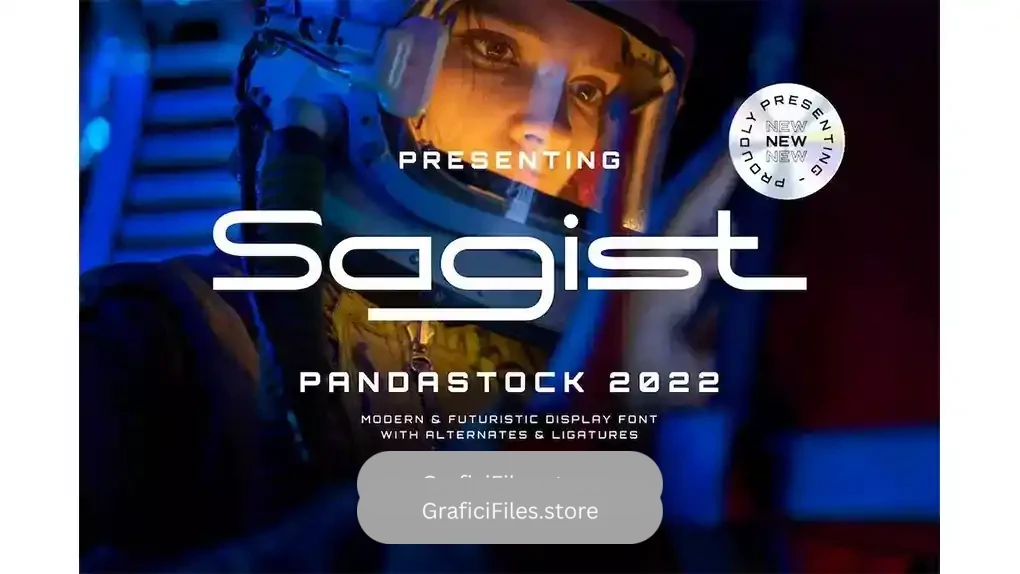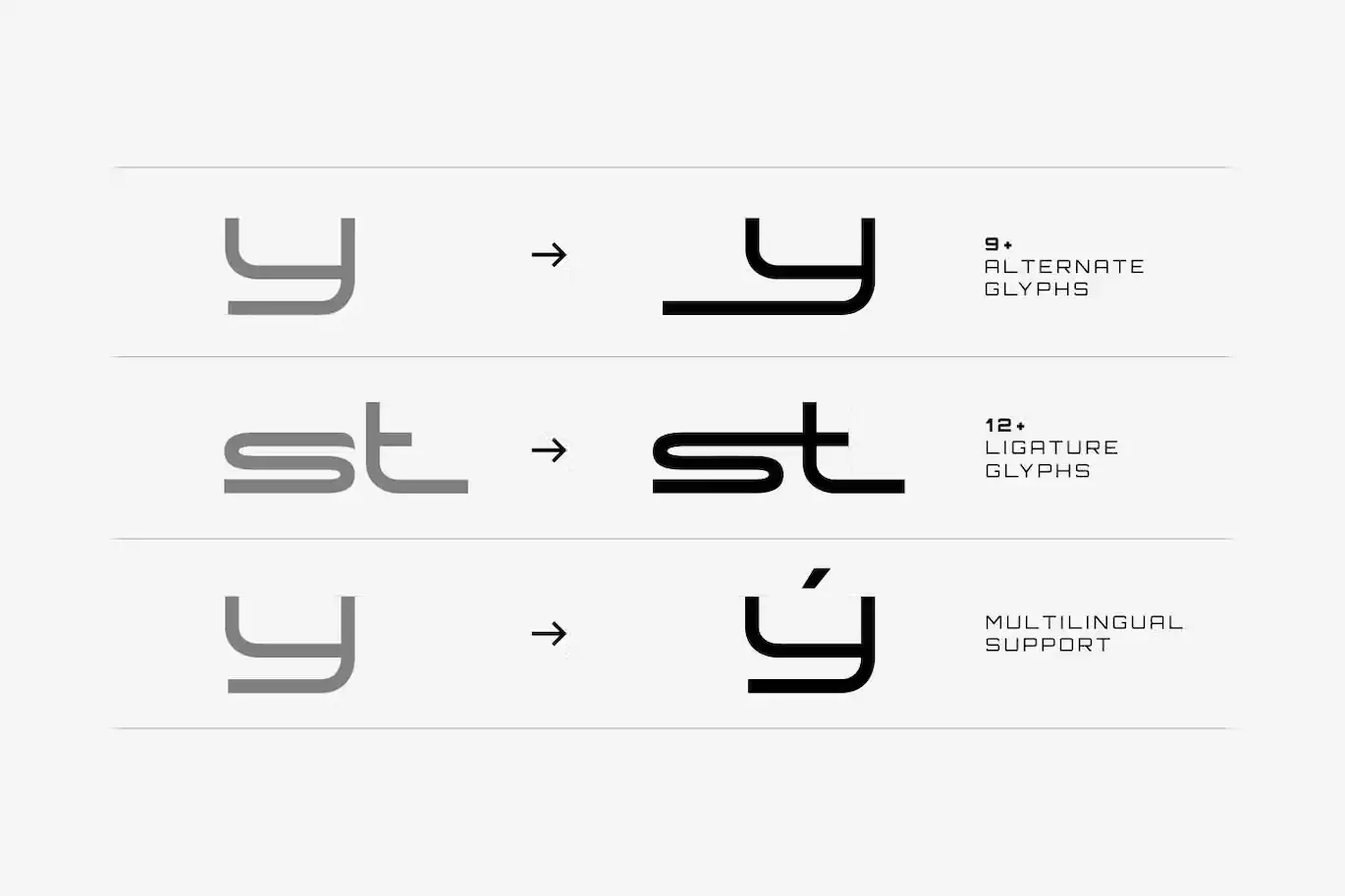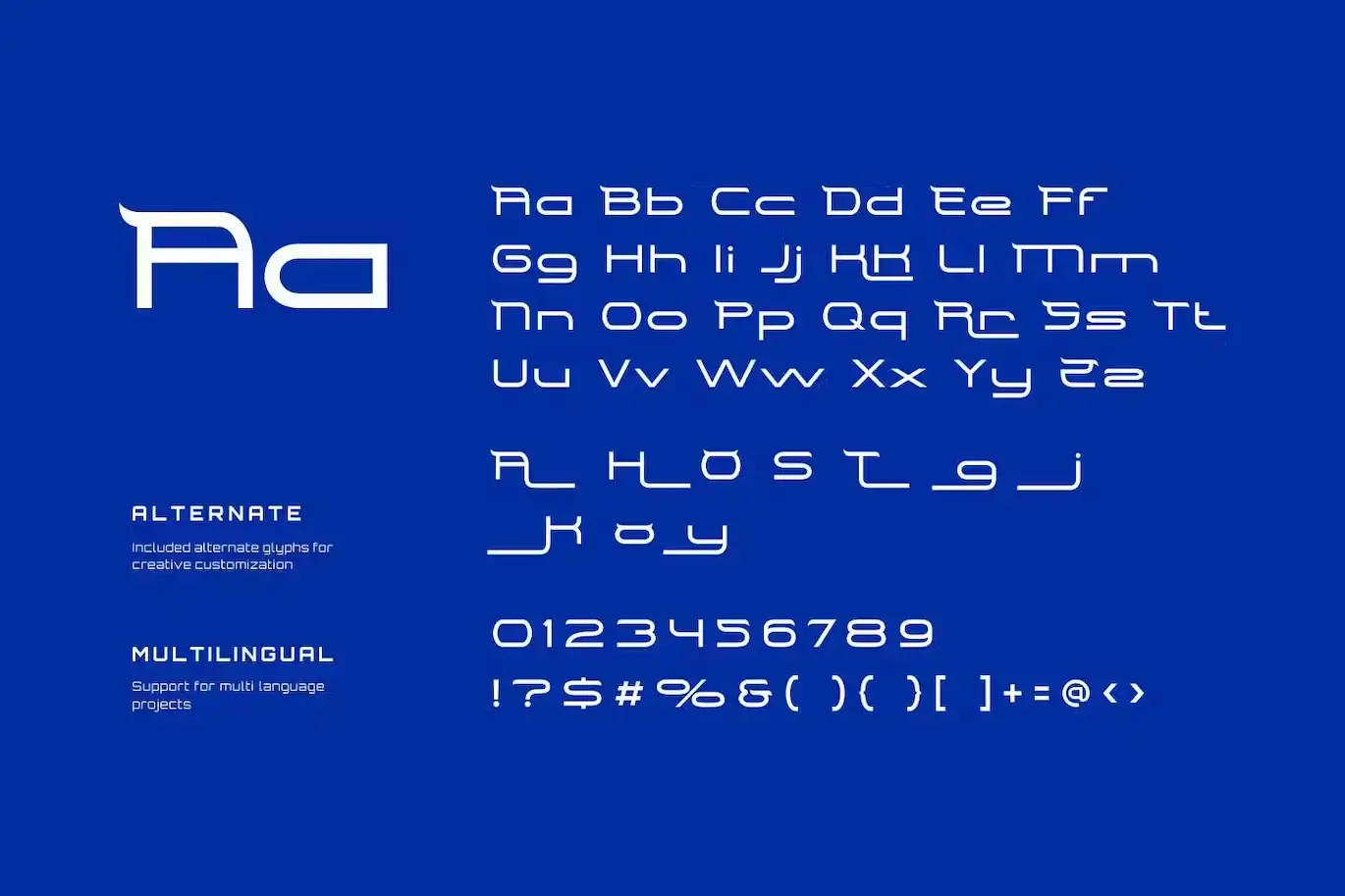
فونت انگلیسی مدرن Sagist – Modern Geometric Sans Serif Font : این مجموعه شامل یک فونت انگلیسی مدرن است که برای دعوت نامه، لوگو، برندینگ، مجله، عکاسی، کارت ویزیت، بسته بندی محصول، ماگ، نقل قول، پوستر، امضا و غیره مناسب میباشد.
- عنوان مجموعه: Sagist – Modern Geometric Sans Serif Font
- فضا بین حروف: معمولی
- اندازه بهینه: بزرگ (نمایش / پوستر)